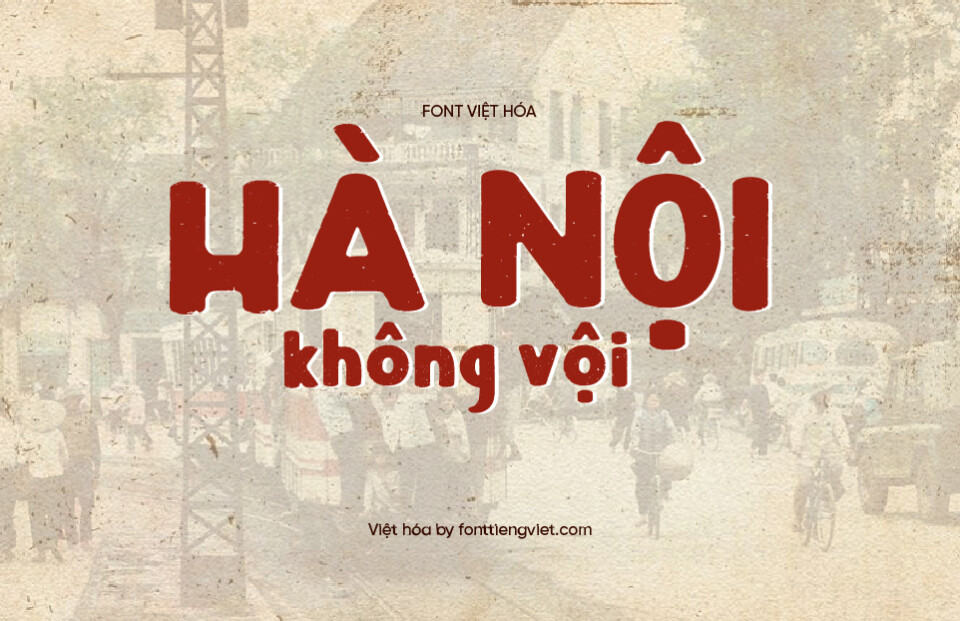
Font Việt hóa 1FTV VIP Hello Sunny
Giới thiệu về bộ Font Việt hóa 1FTV VIP Hello Sunny
Trong thế giới đồ họa hiện đại, việc lựa chọn một Font Miễn Phí phù hợp đóng vai trò quyết định đến tính thẩm mỹ của sản phẩm. Font Việt hóa 1FTV VIP Hello Sunny là một bộ phông chữ mang phong cách hiện đại, trẻ trung và tràn đầy năng lượng tích cực. Được tinh chỉnh kỹ lưỡng về dấu tiếng Việt, bộ font này giúp người dùng dễ dàng truyền tải thông điệp một cách rõ ràng mà vẫn giữ được nét nghệ thuật độc đáo. Đây là lựa chọn lý tưởng cho những ai đang tìm kiếm sự mới mẻ trong thiết kế.
Đặc điểm nổi bật của Font Việt hóa 1FTV VIP Hello Sunny
Bộ Font Việt hóa 1FTV VIP Hello Sunny sở hữu những đường nét thanh thoát, bo tròn mềm mại tạo cảm giác thân thiện và gần gũi. Kiểu dáng của font rất phù hợp cho các dự án thiết kế dành cho học sinh, sinh viên hoặc các nội dung giáo dục sáng tạo. Sự kết hợp giữa tính linh hoạt và khả năng hiển thị tốt trên nhiều nền tảng giúp nó trở thành một công cụ đắc lực cho các nhà thiết kế chuyên nghiệp lẫn người mới bắt đầu.
Ứng dụng thực tế của Font Việt hóa 1FTV VIP Hello Sunny
Sử dụng trong giáo dục và thiết kế sáng tạo
Nhờ vẻ ngoài rạng rỡ như ánh nắng, Font Việt hóa 1FTV VIP Hello Sunny thường được ứng dụng để làm tiêu đề bài giảng, bìa sách giáo khoa hoặc các ấn phẩm truyền thông học đường. Bên cạnh đó, các bạn trẻ có thể sử dụng font này để tạo ra những tấm thiệp chúc mừng, thiết kế áo lớp hay trang trí hình ảnh cá nhân trên mạng xã hội một cách bắt mắt.
Tối ưu hóa nội dung với phông chữ việt hóa
Việc sử dụng Font Việt hóa 1FTV VIP Hello Sunny giúp loại bỏ hoàn toàn lỗi hiển thị dấu câu, mang lại sự chuyên nghiệp tối đa. Bạn có thể kết hợp font này với các tông màu sáng để làm nổi bật nội dung chính, tạo điểm nhấn thu hút người xem ngay từ cái nhìn đầu tiên.